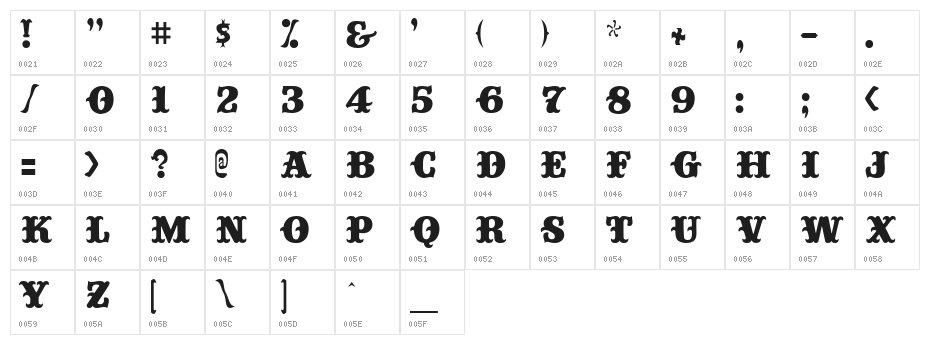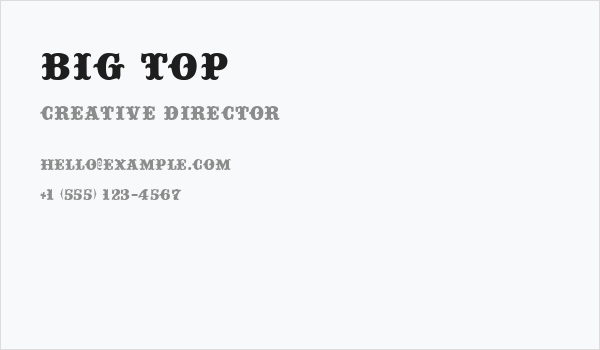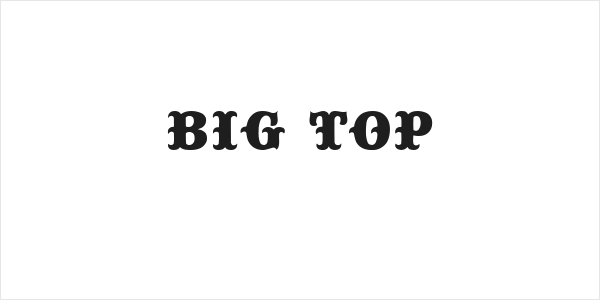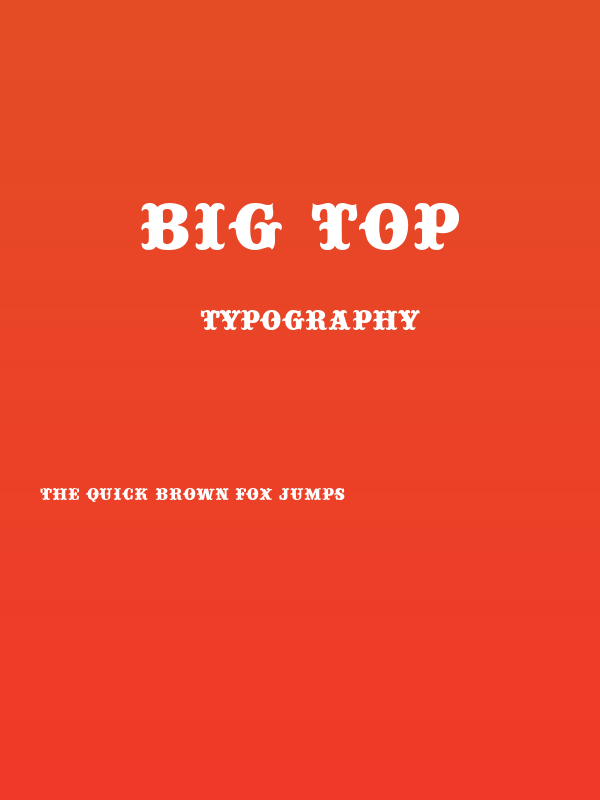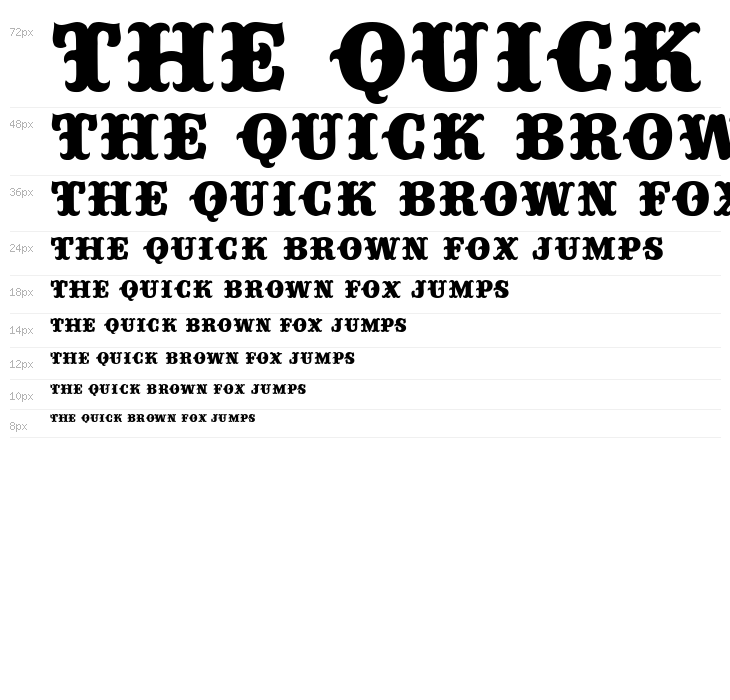
Big Top Font
| Gesamtstil | Vintage |
| Vorgeschlagene Projekte | Ideal for circus-themed posters, vintage advertisements, playful branding, and event invitations. |
Big Top